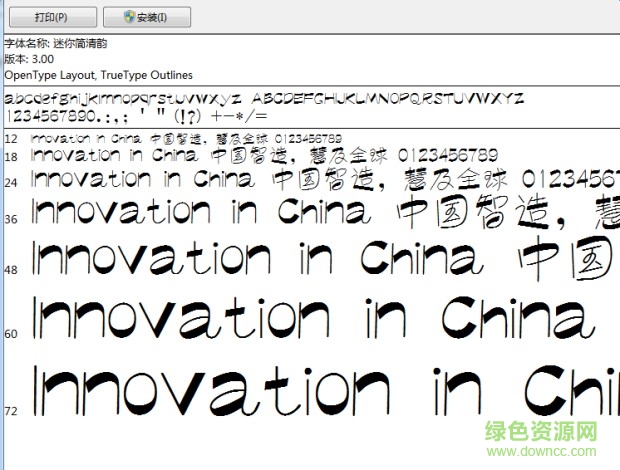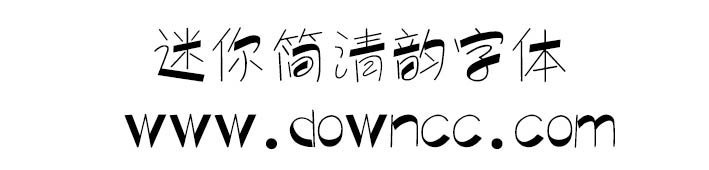
迷你簡(jiǎn)清韻字體一款迷你字庫(kù)中的字體,該字體的粗細(xì)改變突兀,讓人看上去眼前一亮!非常適合用于名片設(shè)計(jì)、廣告設(shè)計(jì)、平面設(shè)計(jì)、雜志報(bào)刊等,有喜歡的朋友可以來(lái)綠色資源網(wǎng)下載使用!
迷你你清韻字體是生活中常用的一種字體,給人以非常清爽的感覺(jué),線(xiàn)條該細(xì)的細(xì)該粗的粗。